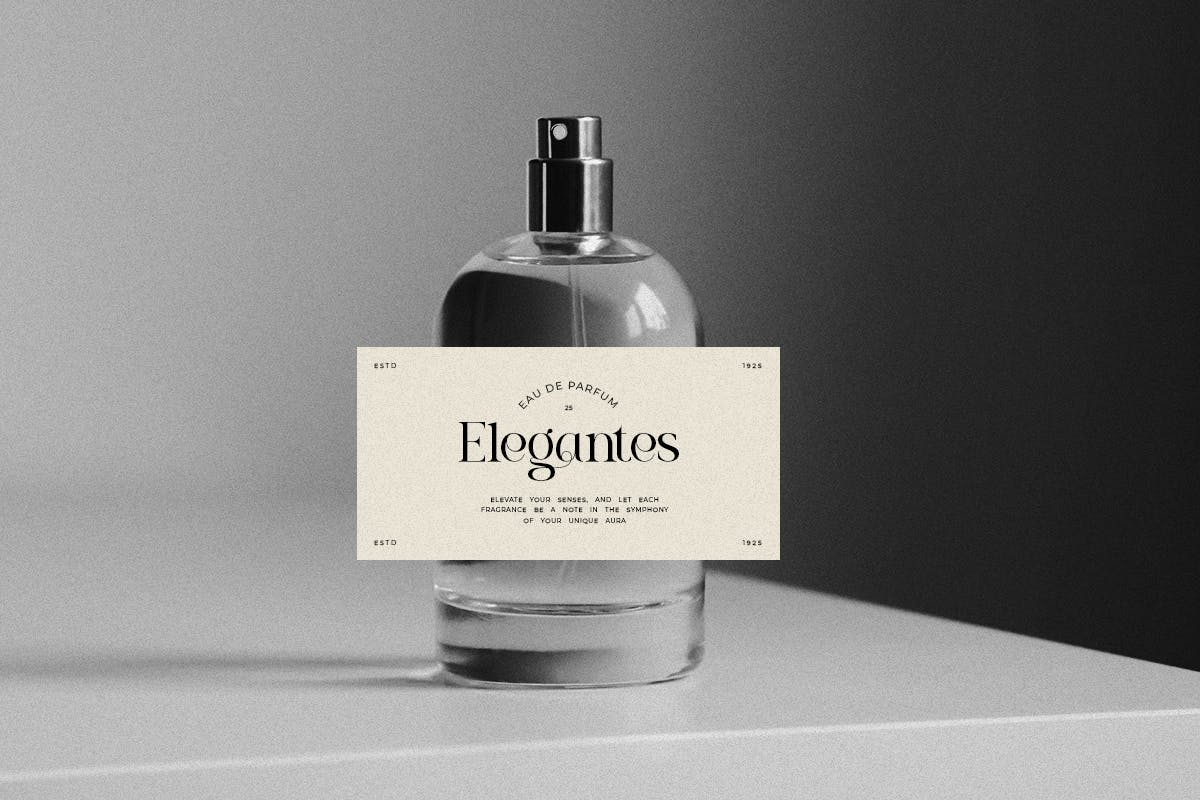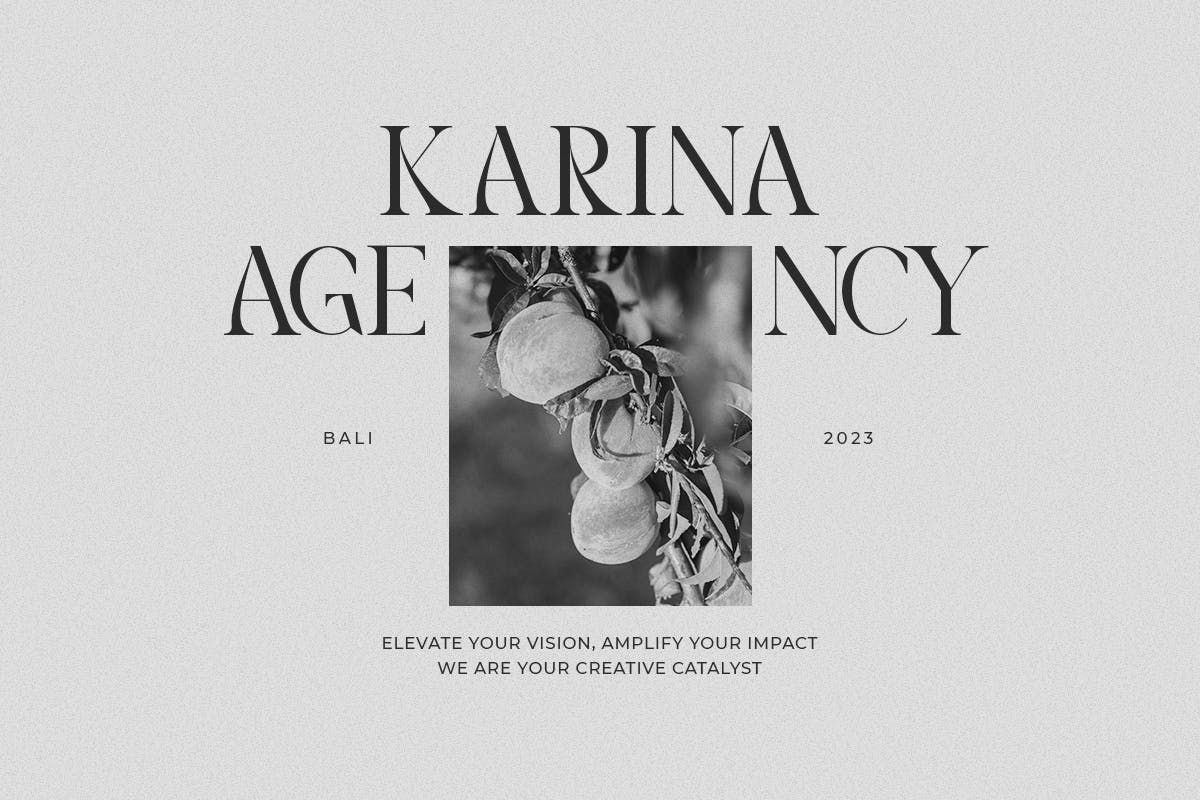
Boho Breeze یک فونت سریف مدرن و شیک است که با طراحی منحصر به فرد و پشتیبانی چند زبانه، کِرنینگ عالی را ارائه میدهد. این فونت برای طراحی لوگوهای لوکس و شیک، طراحیهای ویرایشی کلاسیک، مجلات زنانه، برندهای مد و زیبایی، تبلیغات مدرن، کارتهای دعوت، نقل قولهای هنری، دکوراسیون منزل، عناوین کتاب و جلد، رویدادهای خاص، کیفهای خرید، تیشرتها، تبلیغات و بسیاری موارد دیگر بسیار مناسب است.
ویژگیهای Boho Breeze: